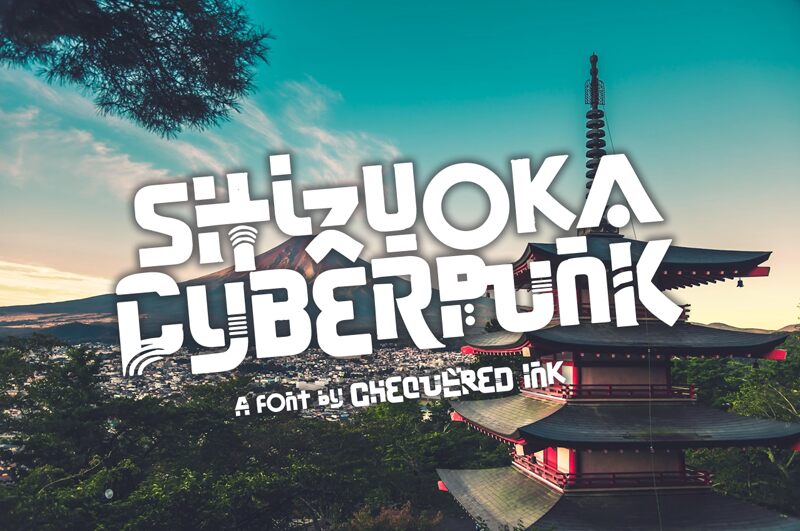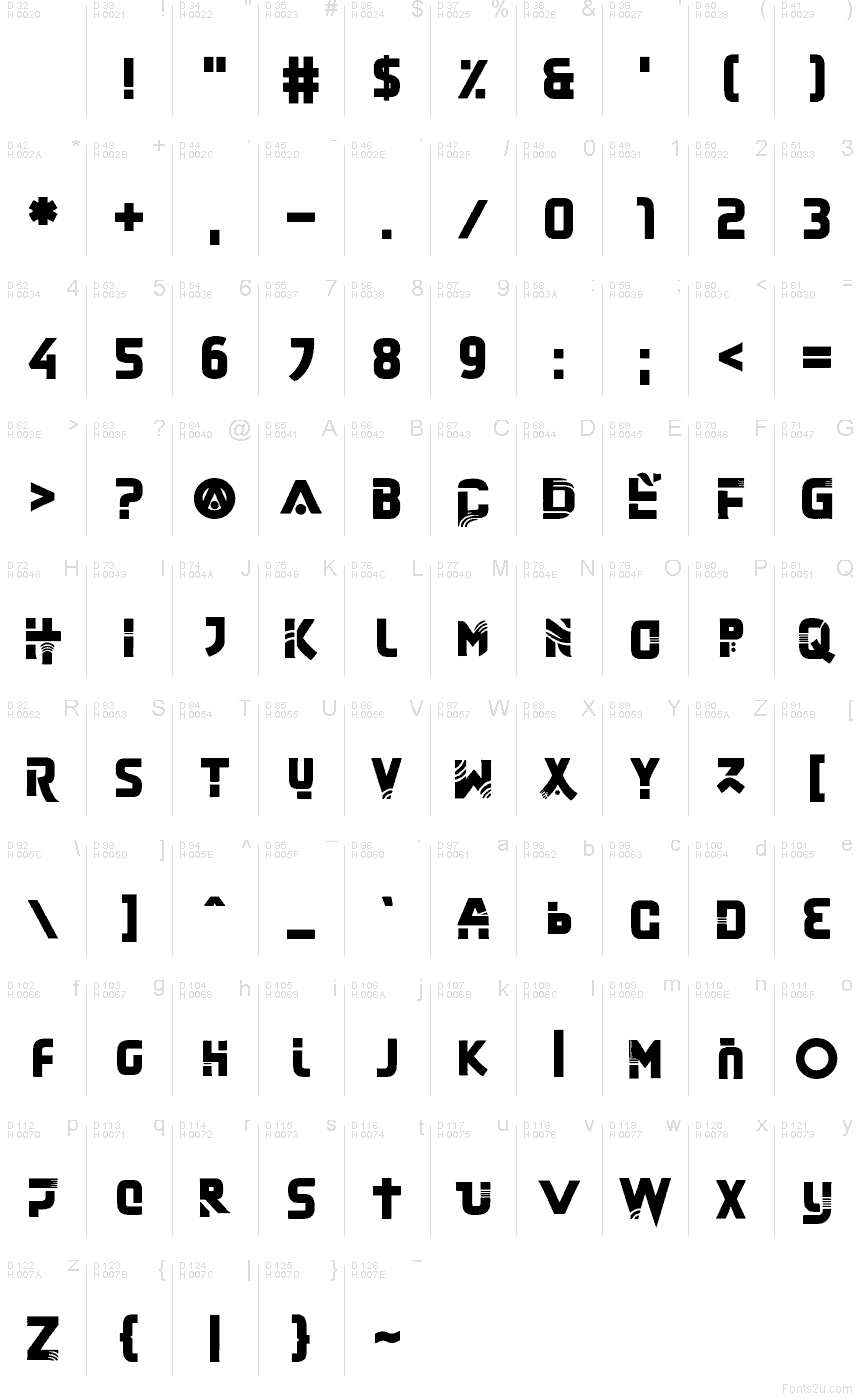
Shizuoka Cyberpunk de Chequered Ink es una tipografía display cyberpunk gratuita, construida a partir de formas macizas, angulosas y cortes geométricos marcados. Su cuerpo robusto se ve interrumpido por detalles de rayas estrechas y líneas de velocidad fluidas, lo que le da al texto el aspecto de cartelería futurista con un toque manga-tech lleno de energía.
Utiliza esta fuente gratuita para títulos de juegos, pósteres de estética anime, portadas de música y gráficos de streetwear. Funciona especialmente bien en titulares cortos y tarjetas de título, donde sus siluetas amplias captan la atención, mientras que los acentos cortados y las marcas de movimiento curvas recompensan una observación más detallada.